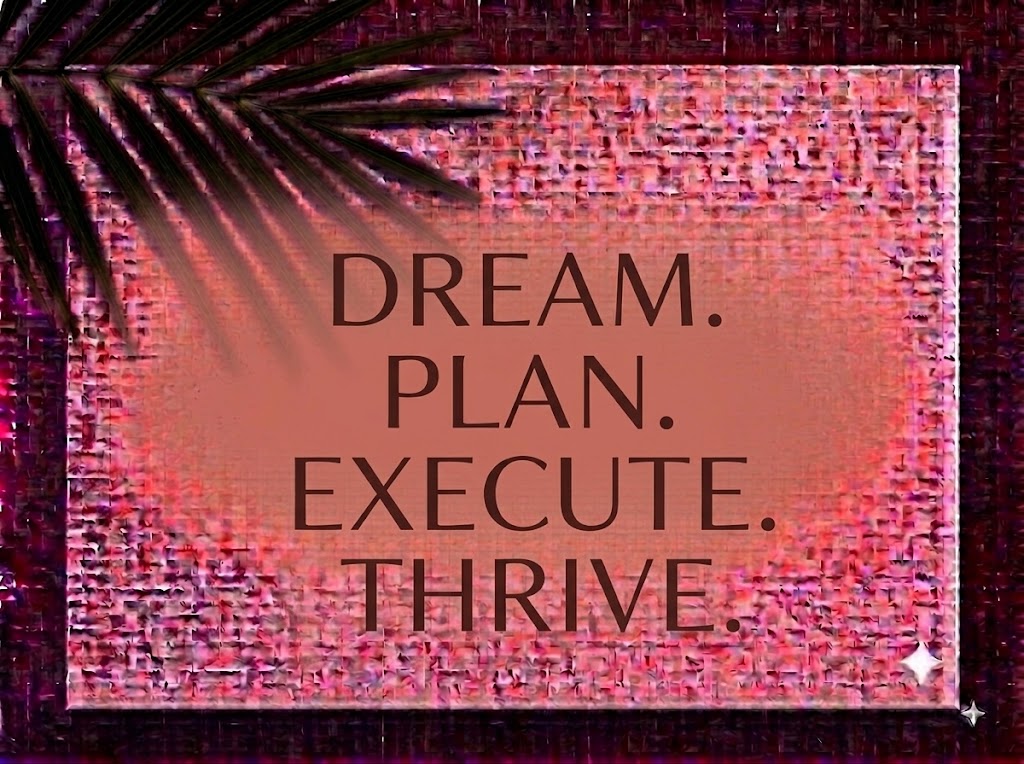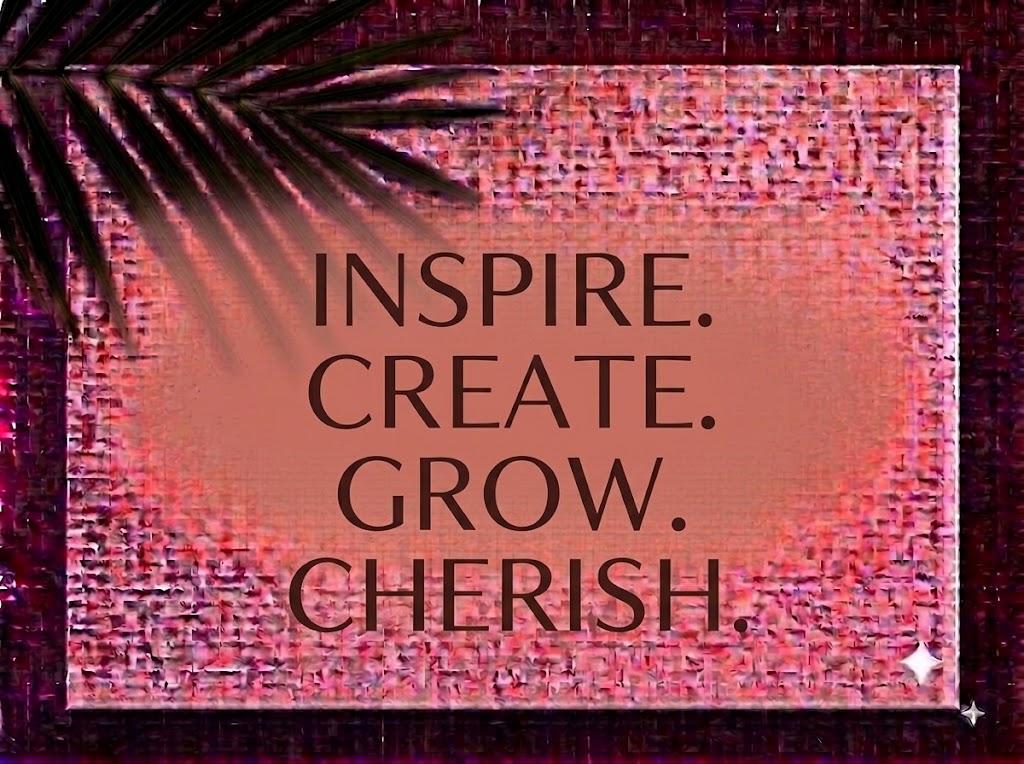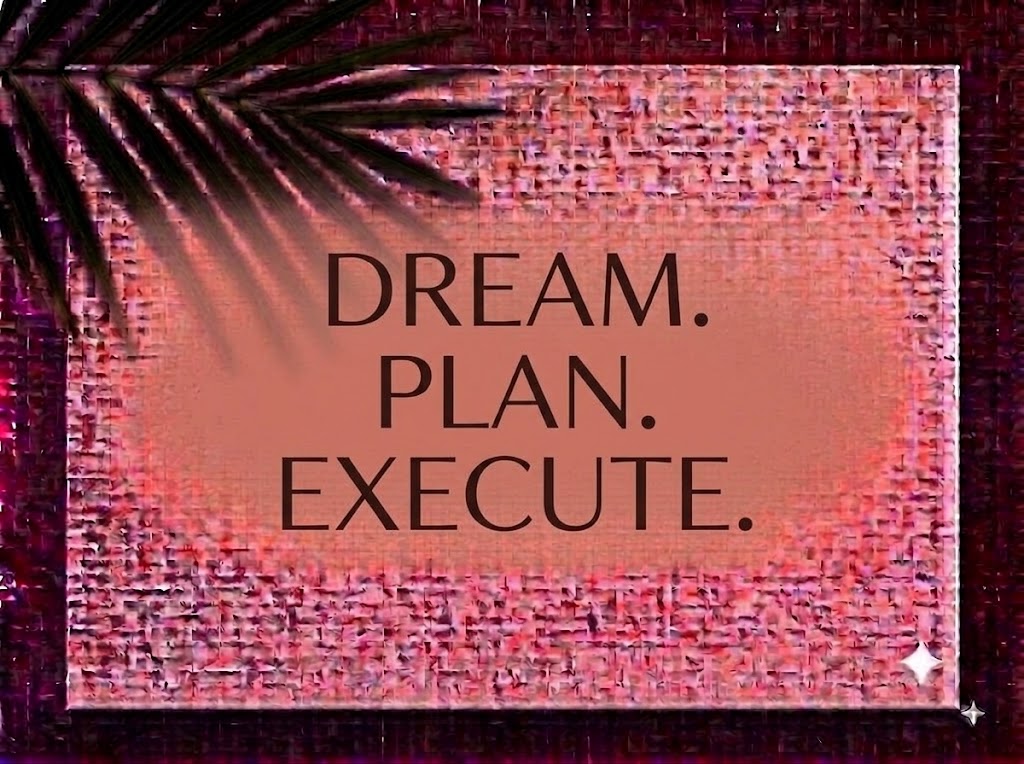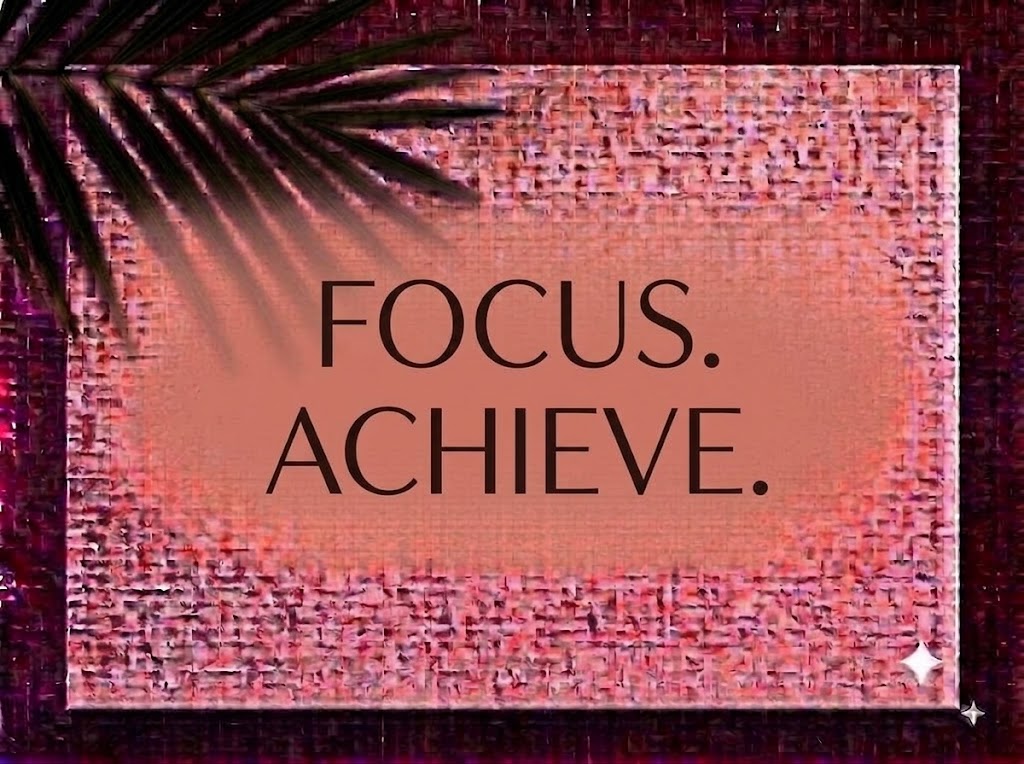
1FTV Lattiva
Trong xu hướng thiết kế đồ họa đương đại và thẩm mỹ tối giản (Minimalism), những kiểu chữ không chân hiển thị (Display Sans-Serif) mang phom dáng thanh thoát cùng đường nét đơn tuyến (monoline) luôn tạo dựng được ấn tượng thị giác tinh tế và cao cấp.
Nếu bạn đang tìm kiếm một phông chữ không chân thanh lịch, hiện đại để thiết kế nhận diện thương hiệu thời trang, bao bì mỹ phẩm, poster kiến trúc hay tiêu đề video ngắn phong cách aesthetic, font 1FTV Lattiva chính là sự lựa chọn không thể bỏ qua.
Giới thiệu về font 1FTV Lattiva
Font 1FTV Lattiva là bộ chữ hiển thị không chân mang phong cách Modern Minimalist Sans, nổi bật với cấu trúc hình học chuẩn xác kết hợp cùng các đường bo cong mềm mại:
Tên phông chữ: 1FTV Lattiva
Đặc điểm nổi bật của ngôn ngữ thiết kế Lattiva
Sức hút thị giác của font 1FTV Lattiva đến từ phom dáng thanh mảnh quý phái cùng cấu trúc hình học tối giản:
Đường nét đơn tuyến thanh mảnh (Clean Monoline): Trọng lượng nét mảnh mai với độ dày đồng nhất xuyên suốt bộ chữ mang lại cảm giác nhẹ nhàng, thông thoáng và đậm chất duy mỹ hiện đại.
Cấu trúc hình học bo tròn mềm mại (Geometric Curves): Các ký tự tròn như
o,e,c,a,b,d,p,qsở hữu các đường cong nở rộng đầy đặn, tạo nên nhịp điệu đọc êm ái, thân thiện nhưng vẫn giữ được vẻ kiêu kỳ, sang trọng.
Tối ưu hiển thị và dấu tiếng Việt từ 1FTV
Để phông chữ vận hành mượt mà trên cả hai hệ điều hành Windows và macOS, phiên bản này đã được tinh chỉnh kỹ lưỡng về mặt thông số nội tại:
Khoảng cách ký tự (Kerning): Khoảng hở giữa các chữ cái được tính toán rộng rãi, giúp các đường nét mảnh mai khi đứng cạnh nhau luôn giữ được khoảng thở tối ưu, không bị dính nét hay rối mắt.
Hệ thống ký tự đồng bộ: Tích hợp trọn vẹn bộ chữ in hoa, in thường, dãy số 0-9 phom dáng hiện đại cùng đầy đủ các ký hiệu toán học và dấu câu cơ bản.
Đánh giá hiển thị thực tế
Khả năng hiển thị của phông chữ được tối ưu linh hoạt theo nhiều kích cỡ:
Kích thước nhỏ (12pt – 24pt): Nhờ cấu trúc khung chữ thoáng đãng và đường nét rõ ràng, các đoạn trích dẫn ngắn hay dãy số vẫn hiển thị rành mạch trên màn hình điện thoại di động.
Kích thước lớn (36pt – 72pt): Đây là đất diễn lý tưởng nhất để 1FTV Lattiva phô diễn toàn bộ vẻ đẹp tinh gọn, thanh tao và thần thái sang trọng của phong cách Minimalist Sans cho các dòng headline chính.
Ứng dụng trong thiết kế đồ họa và sản xuất video
Sở hữu nét cá tính thanh nhã và đậm chất thời thượng, font 1FTV Lattiva mở ra không gian ứng dụng phong phú:
Video ngắn (TikTok, Reels, Shorts): Dáng chữ Sans-Serif thanh mảnh hiển thị rất cuốn hút trên khung hình đứng tỷ lệ 9:16.
Ảnh thu nhỏ YouTube (Thumbnail): Lựa chọn tuyệt vời cho các kênh làm nội dung về Lifestyle, kiến trúc, thiết kế, thời trang hay âm nhạc acoustic lofi chill.
Nhận diện thương hiệu & Bao bì cao cấp: Rất thích hợp làm logo dạng chữ, bao bì mỹ phẩm organic, nến thơm, nhãn chai nước hoa hay thương hiệu thời trang thiết kế tối giản.